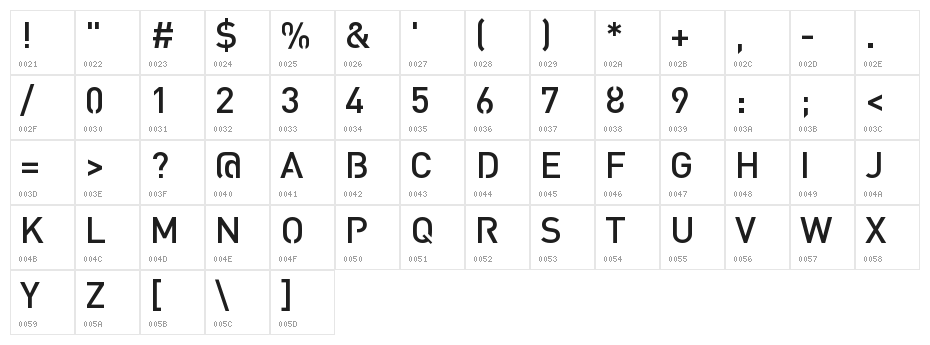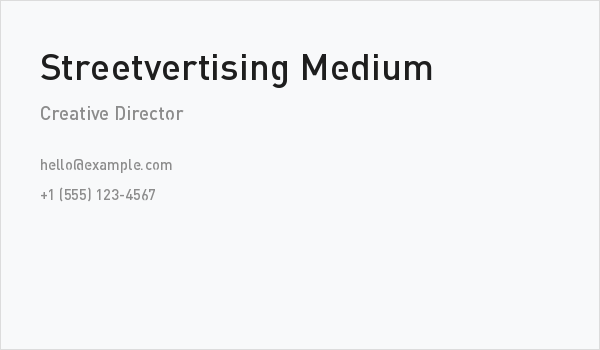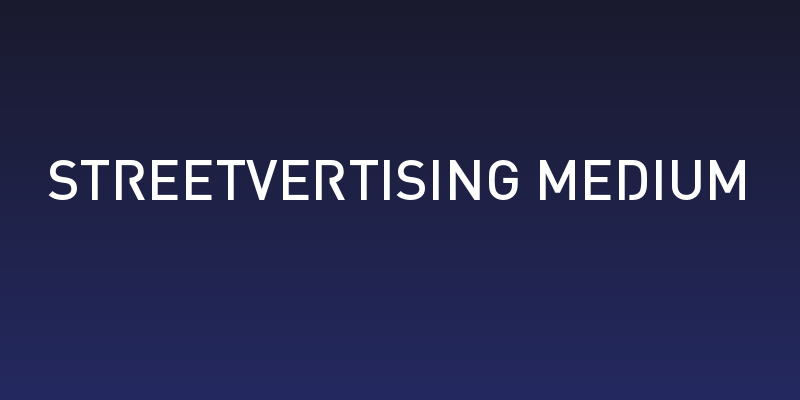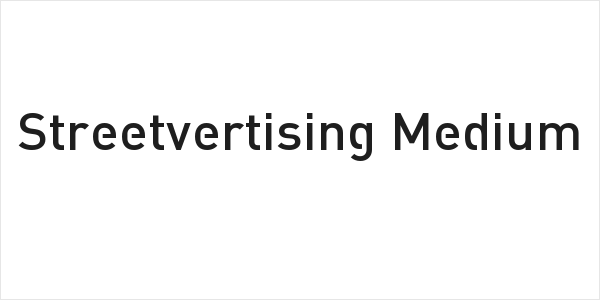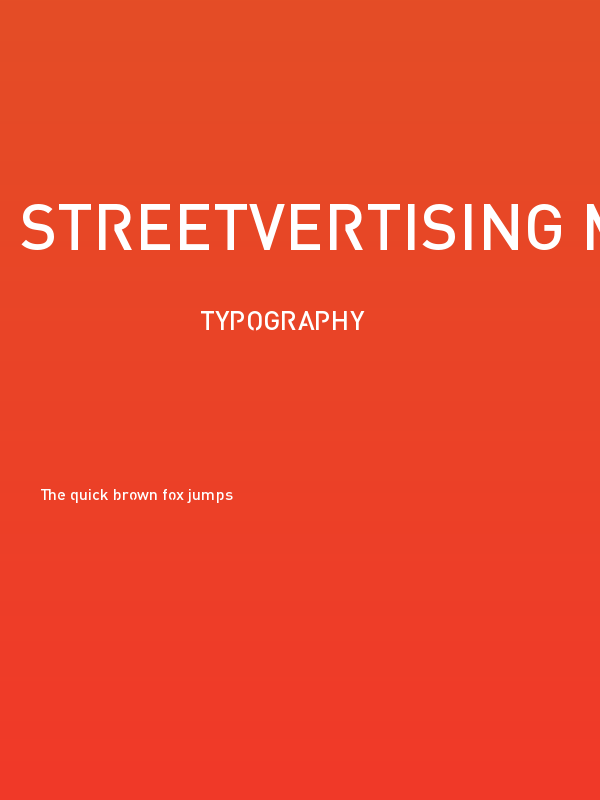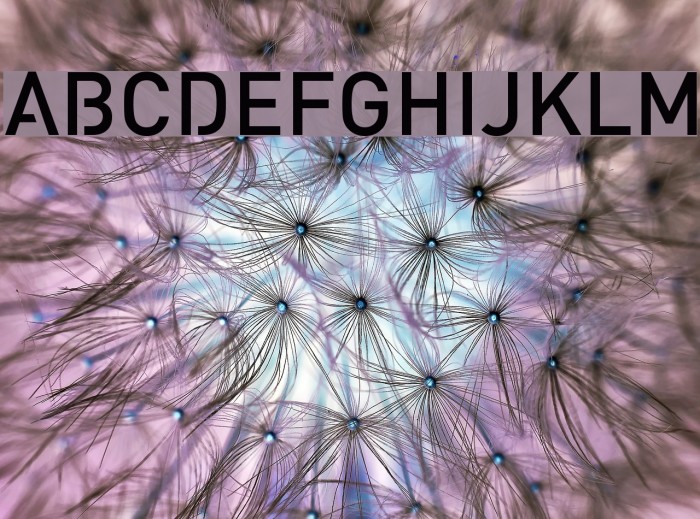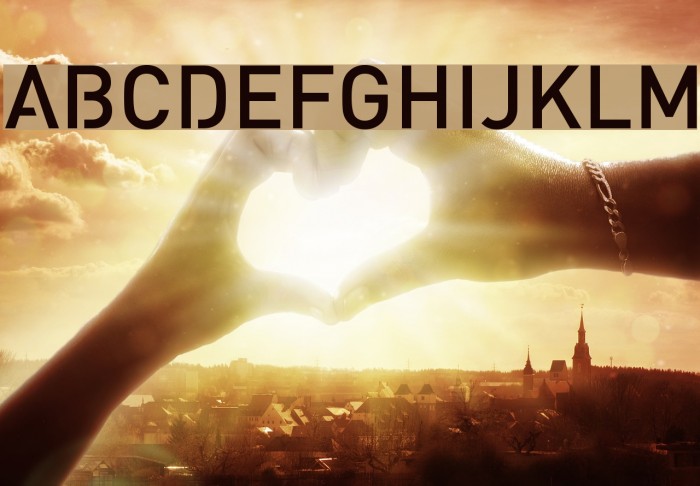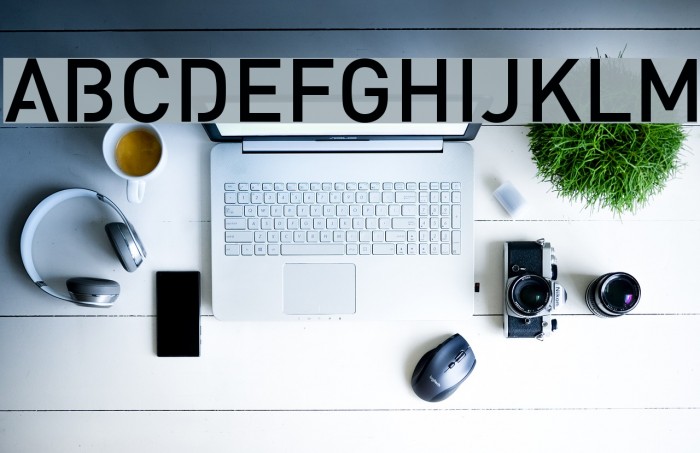
Streetvertising Medium Font
| Progetti proposti | Ideal for branding, advertising, signage, and digital interfaces due to its clarity and modern appeal. |